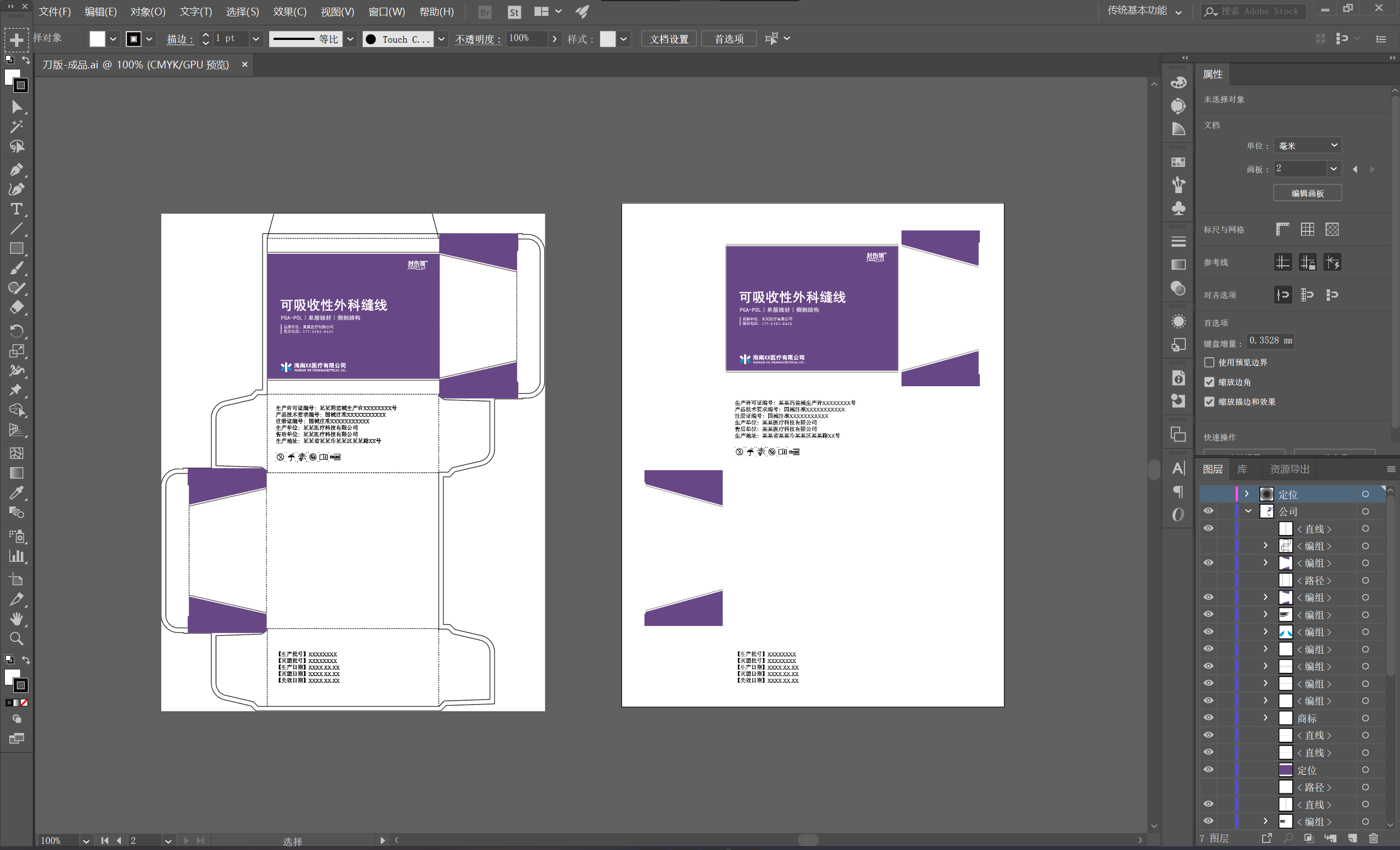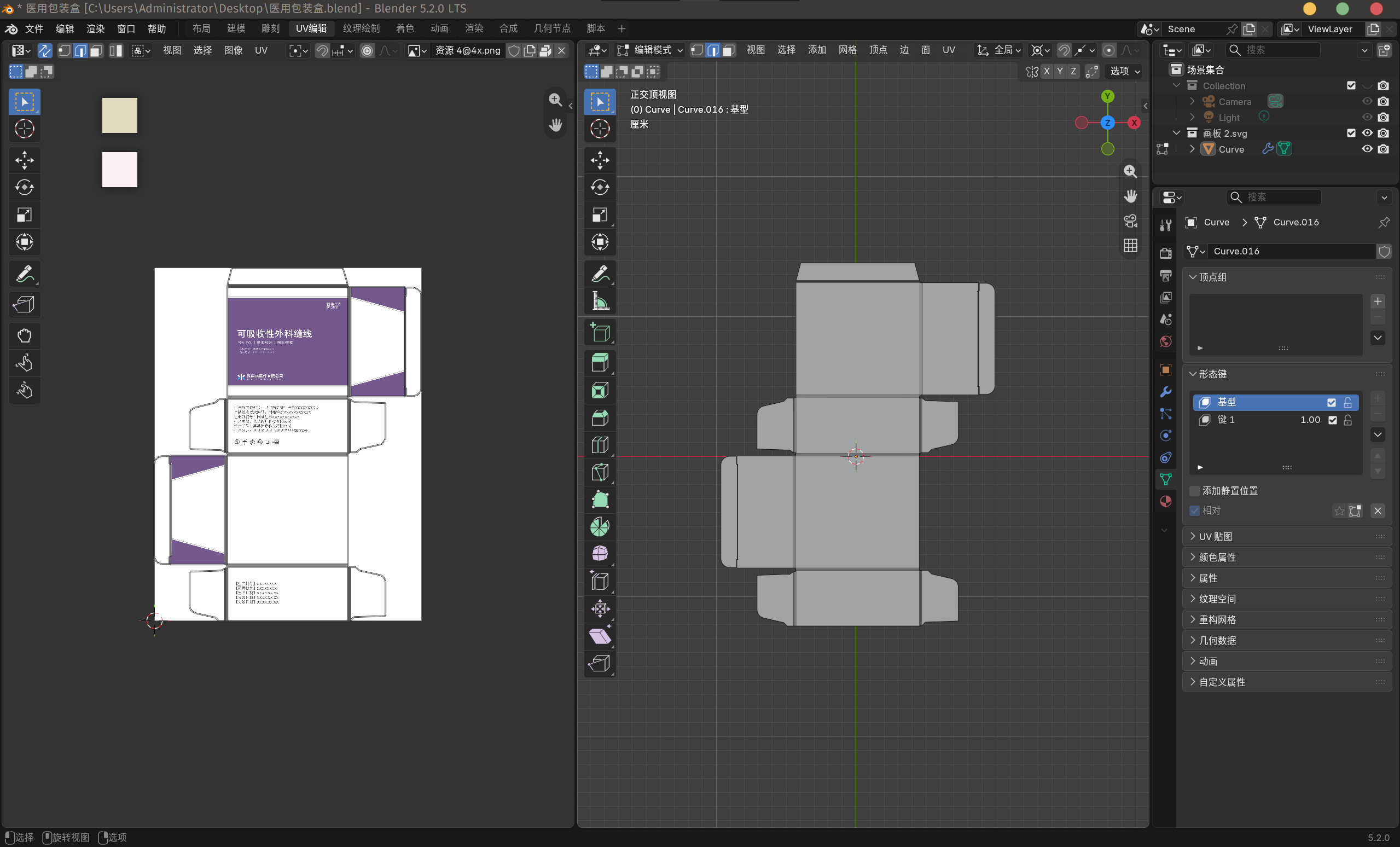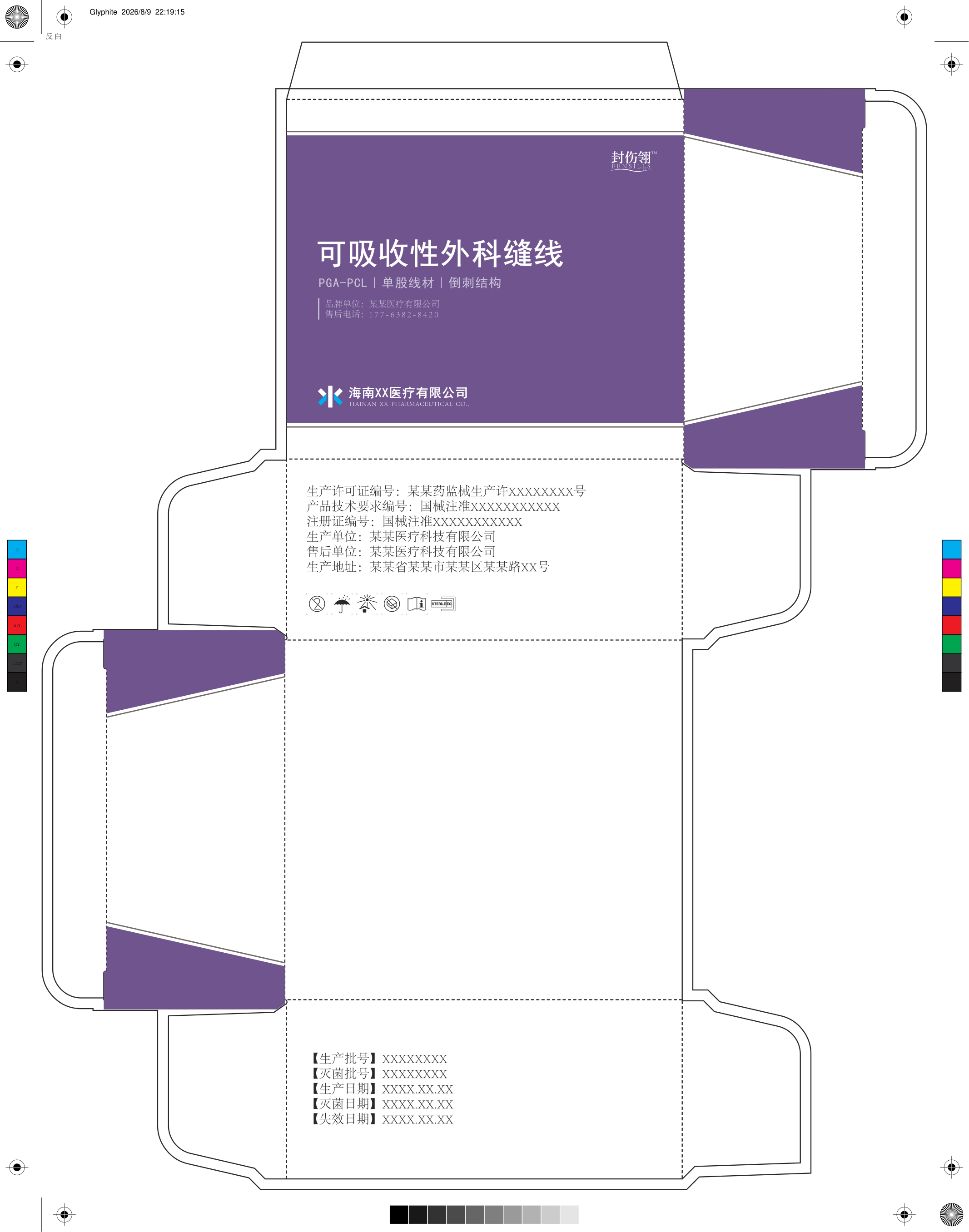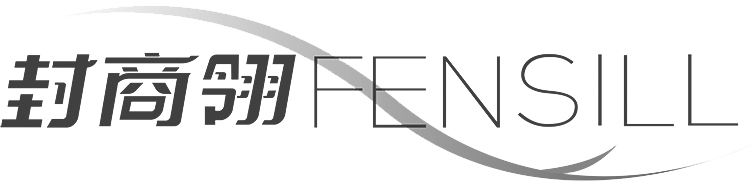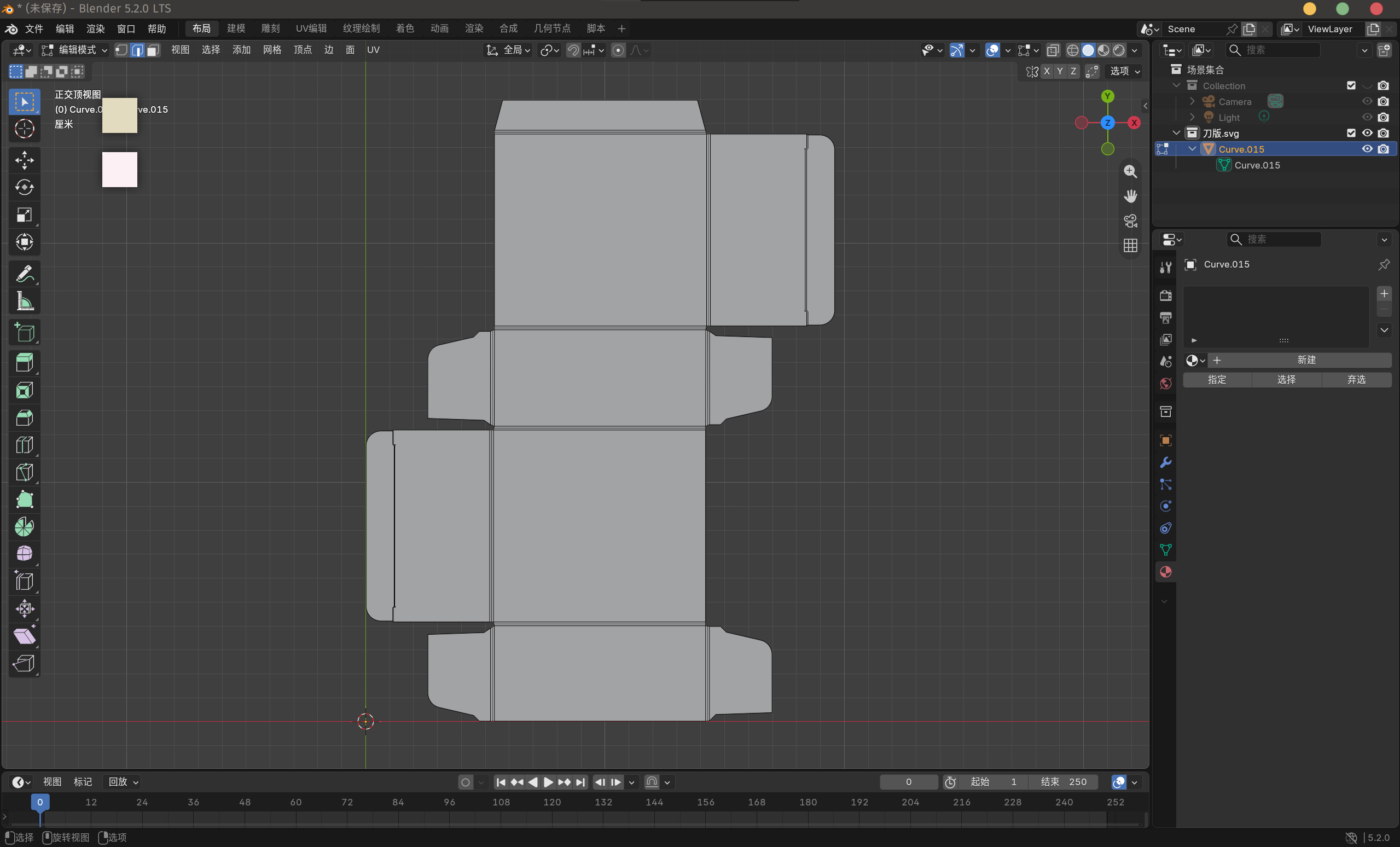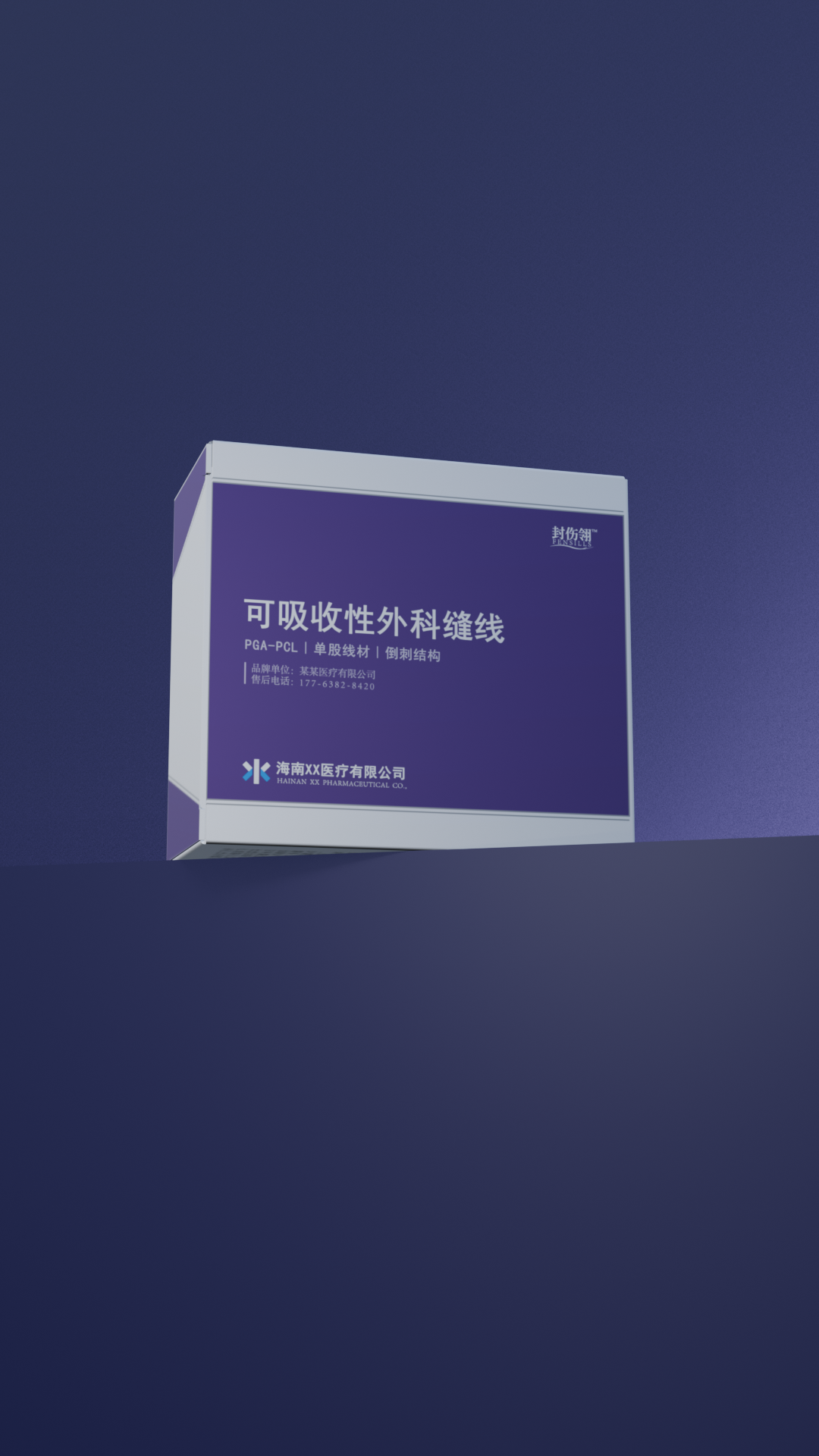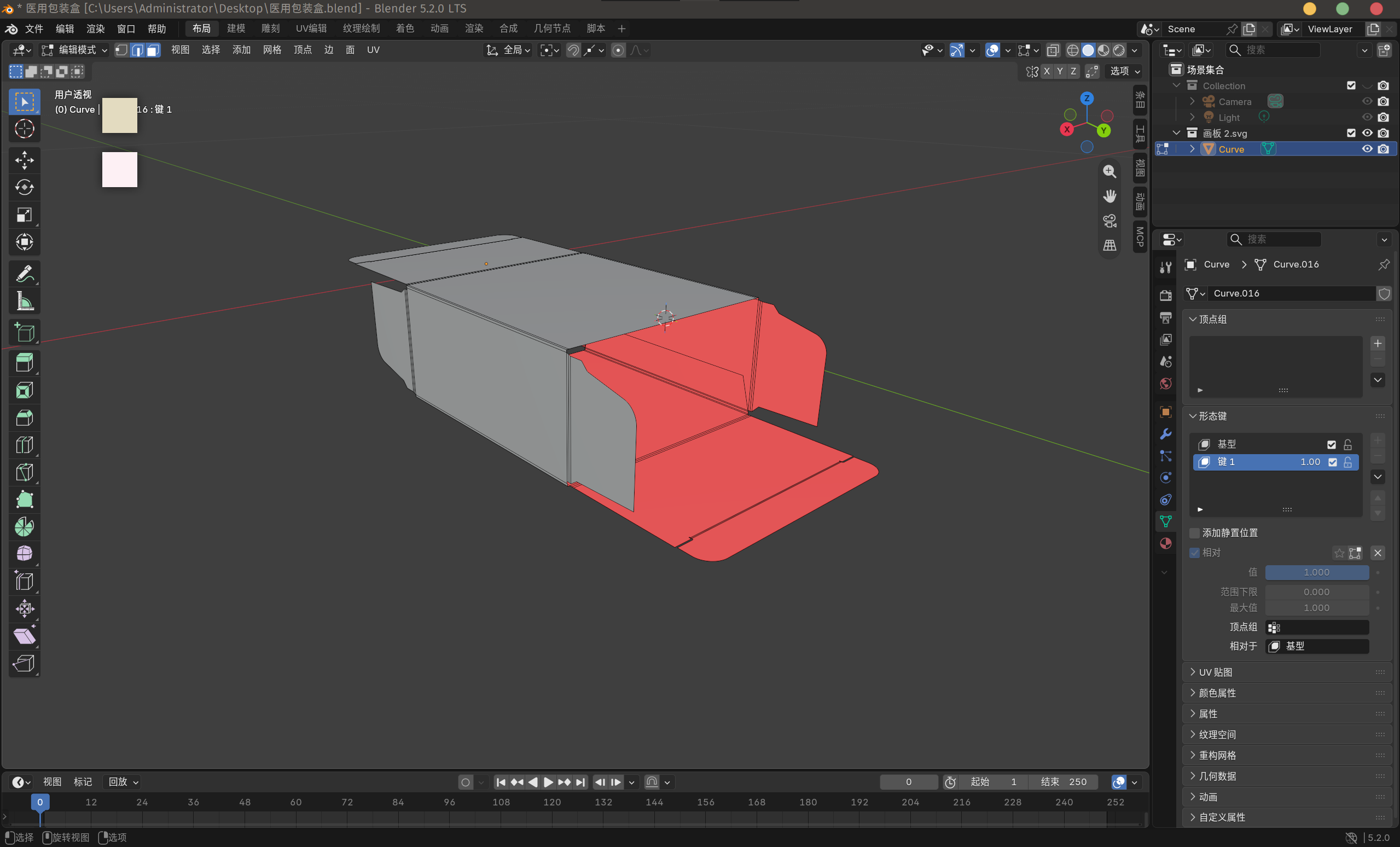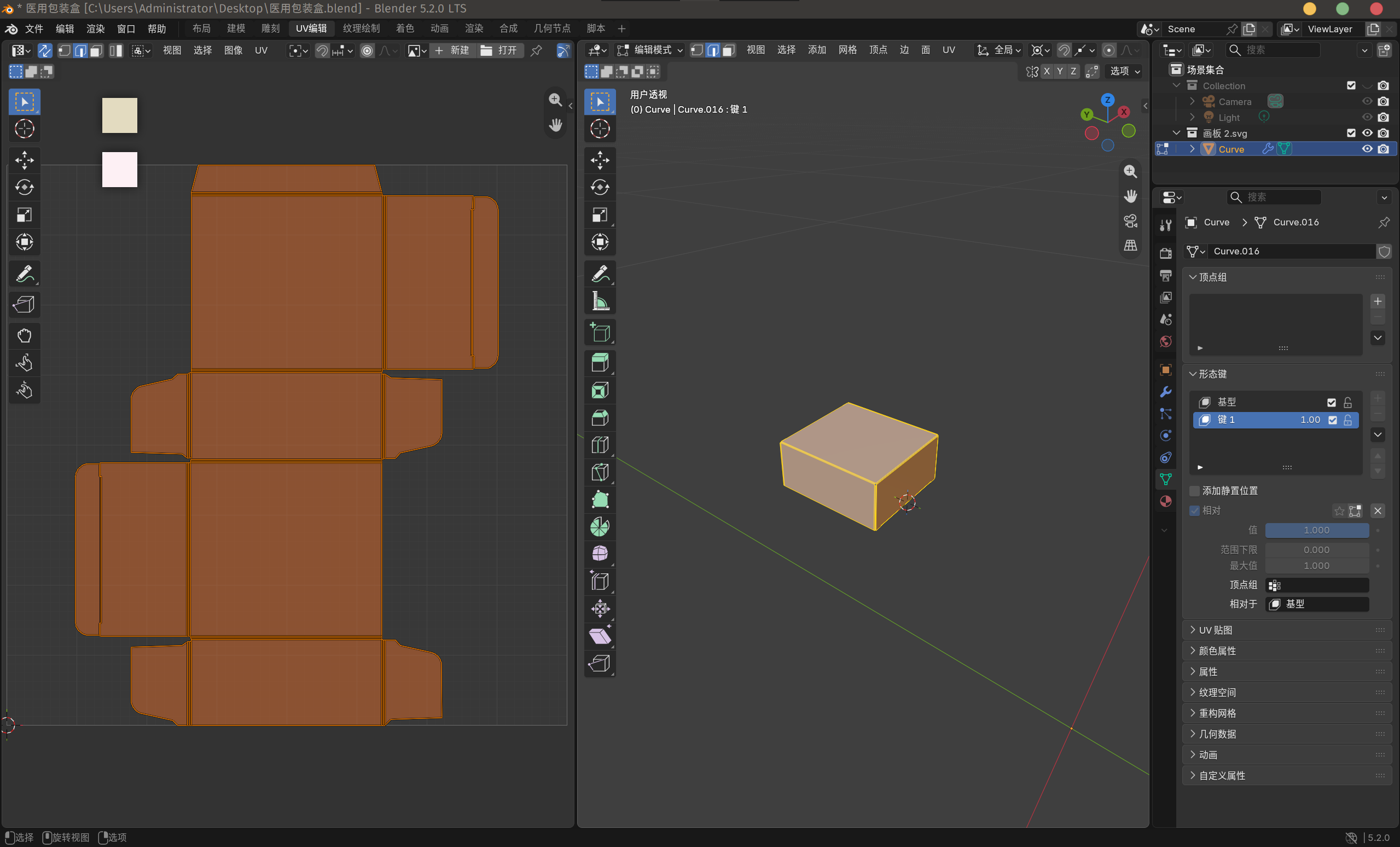
医用品包装系列
各位好~ 最近在筹划制作一套医用品包装,所以写了这篇文章。
和化妆品包装那篇一样,这篇文章也是从零开始的包装设计记录,只是这次的产品换成了医疗器械。
医疗器械和化妆品在包装设计上的侧重点截然不同:化妆品追求的是品牌调性和审美体验,而医用品包装首先要满足的是安全性和合规性,其次才是视觉设计。毕竟这类产品的使用场景更严肃,用户对产品的信任度很大程度上来自包装传递出的专业感。
所以这次的设计思路会偏向简洁、专业、可信赖的方向,尽量减少花哨的装饰元素。
盒型选择
本次包装整体结构为外包装盒 + 内包装袋 + C 型缠线架。外包装盒选择的是反向插锁盒(Reverse Tuck End,简称 RTE),负责承担防护与展示功能;内包装袋采用纸塑透析复合结构,灭菌气体穿透顺畅、排气均匀、灭菌残留挥发速度快,是外科缝线通用的包装结构,适合常规分装缝线;C 型缠线架用于固定线体,避免运输中散乱或损伤倒刺。
包装盒刀版结构图从包小盒网站获取:选中目标盒型后,按F12打开浏览器开发者工具,在DOM中查找特征为 viewBox="0 0 1 1" 且 width="1mm"、父级节点未隐藏的SVG元素,复制出来即可使用。
这个盒型是较为常用的方案,不会增加消费者的打开难度,工艺成熟、成本低。其两端插舌反向互锁,底部受压越压越紧,运输途中不容易弹开;组装无需胶水,单片纸板折叠即可,适合中大批量生产;正面完整无接缝,适合印刷产品信息且能直立展示。
产品了解
这次包装的产品是可吸收PGA-PCL倒刺线,商品名”封商翎”,属于第二类医疗器械。
产品基本情况如下:由75%乙交酯和25%己内酯的共聚物制成,是无菌可吸收性单股带倒刺缝线,无需打结即可缝合组织。线体无涂层,紫色(D&C紫色2号),有效张力支撑时间约14-21天,完全降解吸收时间约90-120天。分为带不锈钢针和不带针两种型号。
产品特点主要是单股结构无组织拖拽效应、线体柔软减少组织损伤、PGA-PCL材质组织反应小、吸收时间短无异物残留。适用于软组织缝合。
法规要求
医疗器械包装设计主要依据两部法规:《医疗器械说明书和标签管理规定》(总局令第6号)和《医疗器械监督管理条例》。
类别 要求
标签必须包含的信息 产品通用名称,须与注册证一致(第八条);型号规格、注册人及生产企业信息与许可证编号、注册证编号、产品技术要求编号、生产日期和使用期限、特殊储存运输条件(第十条);禁忌症及注意事项(第十一条)。无菌产品须标明灭菌方式及灭菌包装损坏后的处理方法,一次性使用产品须注明”一次性使用”字样或符号(第十一条)。
文字与符号要求 文字须使用中文,可附加其他文种但以中文表述为准,文字符号须准确清晰规范(第九条);符号和识别颜色须符合国家相关标准如ISO 15223-1、GB/T 191(第六条)。字高方面,第6号令未规定具体数值,但第九条要求”清晰”,实际注册审评中通常要求正文字高不低于1.8mm、警示语不低于3mm,警示语须用黑体加粗或红底白字以形成对比。标签材料须适应运输储存环境,确保不脱落、不模糊。部分产品须赋医疗器械唯一标识UDI(《医疗器械唯一标识系统规则》)。
禁止标注内容 不得含有”疗效最佳”“保证治愈”“根治”“完全无毒副作用”等功效断言或保证;不得含有”最高技术”“最先进”“最佳”等绝对化用语;不得说明治愈率或有效率;不得与其他企业产品功效和安全性相比较;不得含有”无效退款”等承诺性语言;不得利用任何单位或个人名义作证明或推荐(第十四条)。
广告要求 医疗器械广告发布前须经审查机关审查并取得批准文号,内容以说明书为准,不得含有虚假、夸大、误导性内容(监督管理条例-第六十条)。包装标签信息属于标签管理范畴,不属于广告审查范围,但仍须确保内容真实准确、与注册证一致。
总结:标签信息要标全(名称、注册证号、生产信息、日期、禁忌症等),以中文为准,正文字高不低于1.8mm(在实际使用中,一般来讲是不小于8pt,正文大多在9.5~10.5pt;小字部分可以使用7~9pt),警示语字高不低于3mm(约10.5pt)并用黑体加粗,符号用国际标准,不能用绝对化用语和疗效保证。
包装设计
首先打开 Illustrator,导入之前的 SVG 刀版图。由于包小盒的刀版已经内置了出血,所以这里不需要再去额外配置出血线的参数。剩下的色彩条、套准、角线等标记在导出的时候会自动生成,所以也不需要处理。
另外,在包装设计时,还应该考虑到叠印和套印是否准确,大部分情况下程序都会自动处理,需要注意的只有字体部分——字体应该尽量使用单黑,然后开启叠印或者正片叠底,这样可以避免因印刷套印不准导致露白现象的发生。
接下来就是正式设计了,首先应该把该写的文本和标识写上(先画图也行,只是我个人觉得医用包装先从文本开始比较好)。根据前面法规要求梳理的内容,需要标注的信息包括:商品名称”封商翎”及产品名称”可吸收性外科缝线”、型号规格、注册人及生产企业信息与许可证编号、注册证编号、产品技术要求编号、生产日期和使用期限、特殊储存运输条件、禁忌症及注意事项、灭菌方式、”一次性使用”字样或符号等。
商标
其中商标部分,在国家知识产权公共服务平台上查询结果如下图,申请日期2025-10-21,申请号88147508,商标类别为第10类(医疗器械):
不过考虑到我并不是真的在设计产品包装,为了避免可能存在的法律风险,这里虚构一个相似的商标。并且由于是虚构的,所以不能使用®,仅使用™​。最终使用的商标如下图,没进行什么操作,只是对齐了一下字体,修改了文字。
本来还想将缝线加进来的,但是不太好看,于是就此作罢。
符号
也就是灭菌、批号、序列号、制造商、生产日期、EU 授权代表、IVD、乳胶、温度/湿度/气压限制、一次性使用、包装破损禁用、防日光、干燥储存等 ISO 15223-1:2021 符号。正规渠道应该是 ISO Online Browsing Platform,或者也可以去 WQS 医疗器械标识图例 这个网站下载高清标识。
这个参考原包装来放就行,不过我查了一下 ISO 15223-1:2021 的规定,是仅灭菌方式强制注明,而 5.2.6 不得二次灭菌 和 5.2.11 单层无菌屏障系统 这种属于可选项,但如果要放就得一起放,必须紧邻。这里就不放那么多图标了,只放必要的。
画面
考虑到这是医用包装,以功能性为主,包装上就不设计工艺了,毕竟那样会增加成本;颜色上也简单点,就用 PANTONE+ CMYK Coated 就行,用不着专色之类的东西增加成本。
成品
由于没有工艺,这里就直接一张页面就够了。
建模
将裁切边框和折痕复制出来,然后执行以下操作就可以将SVG转化为单独的面板了:
对象→复合路径→建立
对象→路径→轮廓化描边
对象→释放复合路径
取消填充颜色→配置线框颜色→删除底图
再然后就使用分布间距的功能将包装盒的不同部位的间距设置为2mm,实现如下图所示的效果:
接着导入 Blender 就行。执行以下操作即可获得最终可折叠白模:
右下角材质面板→数据→删除材质
右键→转化为贝塞尔曲线(AI的DWG文件导入Blender有BUG,布线会很乱,需要多转化一次解决)
右键→转化为网格→转换为曲线→转化为网格
点击随意一个面,按A全选→Ctrl+J合并
F键填充
Ctrl+R→给刚才的填充面卡线
最终得到的白模效果如下:
然后就是旋转折叠了,选择折痕边作为轴(轴心点设置为3D游标,Shift+S设置游标到选中项),使用快捷键 R 来旋转各个面板。
当然,也可以用骨骼来折叠,骨骼更方便,只是前置准备多了一些,还需要绑定骨骼:
折叠完成后的最终形态:
折叠完成后,进行UV展开并将之前设计好的包装贴图映射到模型上,确保贴图在折叠后的各个面上位置准确、无拉伸变形。
PS:插舌底面那边弄错了方向,实际应该为右图,上下插舌都保持相同的方向。
这里有个细节,我在折叠之前创建了形态键,所以可以回复到平面状态。没有形态键的话折好就回不去了。
另外UV的话,我是用的 从视角投影(限界) 来进行展开,如果提前展开好了不用平铺也行:
最后给模型加上简单的灯光和环境反射,渲染出成品效果图:
另外,在此附上该公司,今年最新产品的包装以供对比参考: